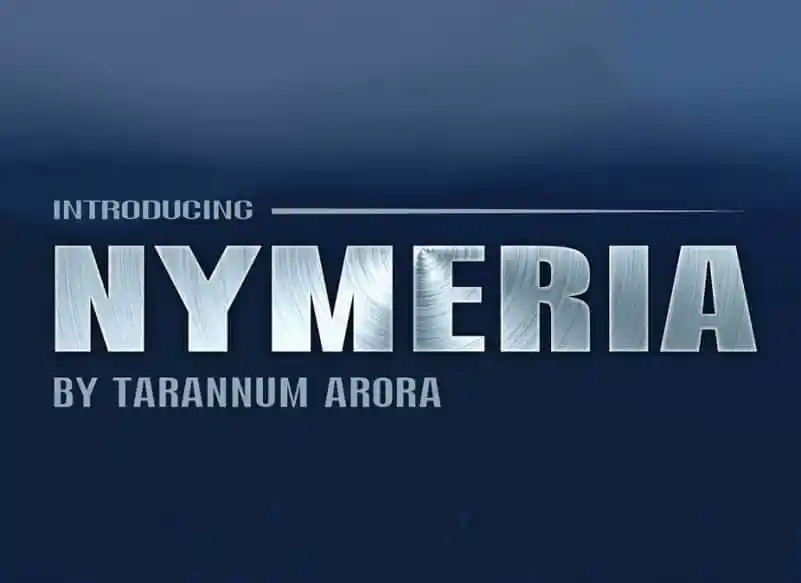
Nymeria Font Family – Download Grátis
Introduzimos a família de fontes Nymeria Font Family, uma tipografia sans serif moderna que oferece flexibilidade para uso em diversas áreas do design. Esta fonte inclui um vasto leque de estilos para ajudá-lo a encontrar o melhor tom para seu projeto. Perfeita para aplicações como postertextos para filmes, headlines e títulos de seção, desenhos de logotipo, banners grandes e designs web clássicos com uma pitada de detalhes decorativos. Ideal para aqueles que buscam um look clean e atual em seus projetos visuais.